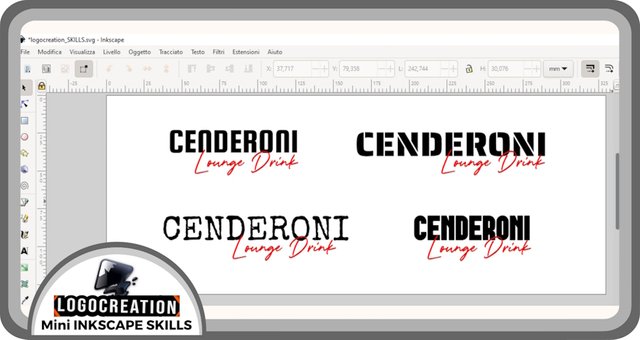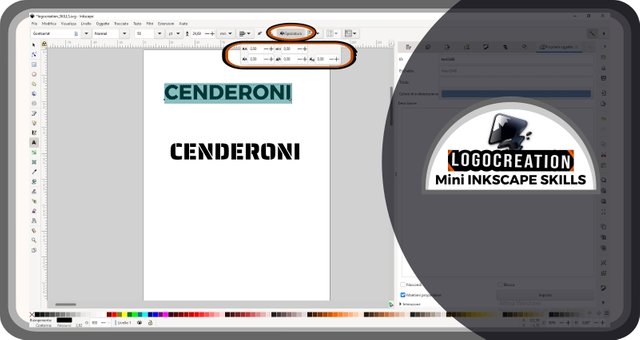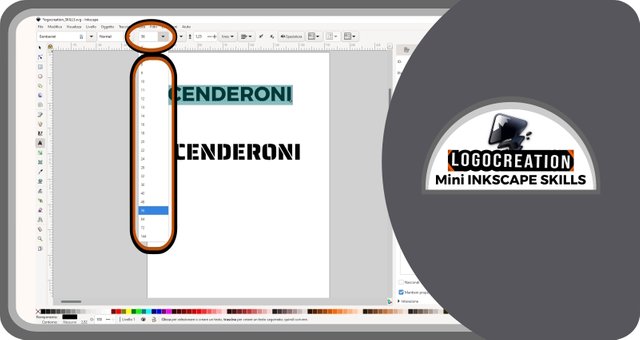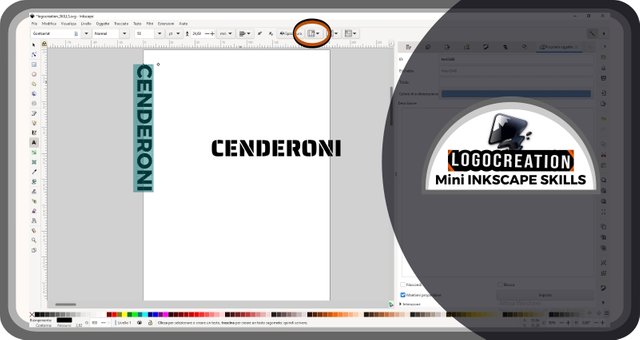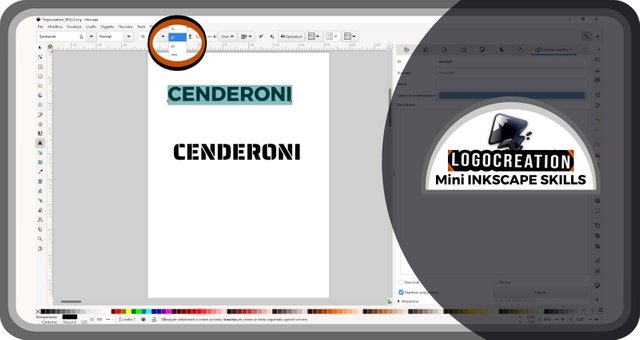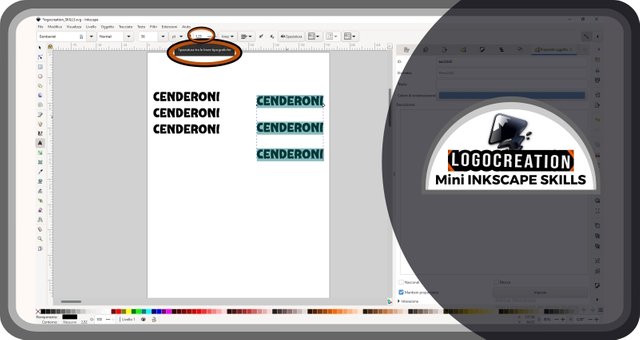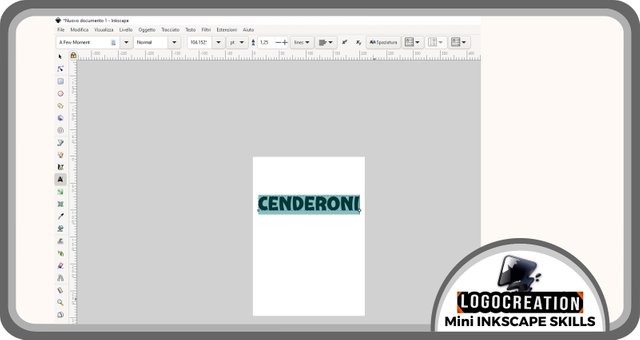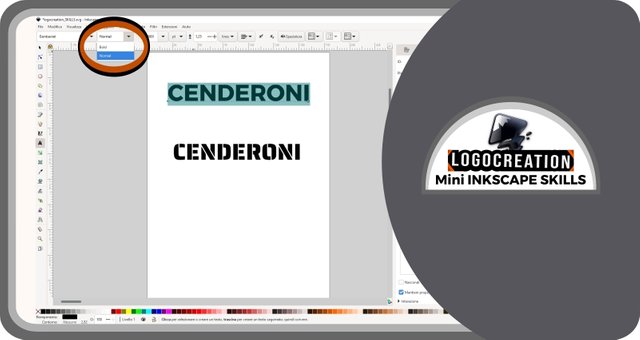
LOGOCREATION - Mini INKSCAPE SKILLS: FONT e CARATTERI TIPOGRAFICI [ITA-ENG]
Oggi torno con il primo vero episodio del mio spazio dedicato alla costruzione di graphic design e all'uso di Inkscape. Un paio di settimane fa ho lanciato l'argomento con un post introduttivo che trovi CLICCANDO QUI. Al suo interno puoi avere notizie riguardo i due fondamenti di questa specie di rubrica:
1. Creazione di loghi ipotetici a titolo di esempio
2. Utilizzo del programma di grafica vettoriale Inkscape
Non torno a ripetere tutto ciò che puoi trovare là, ma sostanzialmente il mio articolo cercherà di mostrare alcune della azioni di base di Inkscape durante la creazione di un logo immaginario; un logo che spesso avrà caratteri giocosi e pertanto invito a non prendere questa caratteristica come volontà di offendere qualcuno (cosa che assolutamente non è nell'intenzione di questi post).
Insomma, procediamo.
LOGO SEMPLICE – Usare i CARATTERI TIPOGRAFICI in Inkscape
Per questo primo appuntamento ho pensato a un logo composto da soli elementi testuali, usando i cosiddetti CARATTERI TIPOGRAFICI, anche definiti FONT. Che cosa indicano questi termini?
Il CARATTERE è ogni elemento comunicativo tra quelli che noi usualmente utilizziamo nella lingua scritta (per intenderci: le lettere, i numeri, la punteggiatura, eccetera). Se noi tracciamo una "a", ecco, quella è un carattere presente in molte lingue scritte occidentali.
Il (o secondo alcuni la) FONT indica invece l'insieme di caratteri tipografici tracciati con una certa morfologia, o ancor meglio con quello che potremmo definire "stile". Questo perché, per esempio, la lettera "a" può essere disegnata in vari modi che mantengono la morfologia fondamentale della lettera "a" ma che la rendono diversa da quella tracciata in uno stile differente. Per questo, quando i caratteri tipografici hanno invaso il mondo digitale, la parola font è stata utilizzata per indicare il file di installazione di una famiglia di caratteri disegnati nello stesso stile.
Questa distinzione netta delle due parole è però stata sconvolta, e – quando utilizzano la locuzione "CARATTERI TIPOGRAFICI" - le persone non stanno indicando gli elementi singoli, bensì il concetto di font (insieme dei caratteri di una data famiglia tracciata seguendo uno stile).
Quindi, per concettualizzare: il "carattere" non è un "font", ma spesso il "font" viene anche chiamato "carattere tipografico" (o, in taluni casi, semplicemente "carattere").
Detto questo... come creare un logo testuale in Inkscape?
Prima di tutto, è bene avere qualcosa da scrivere. Poi, è necessario aprire l'applicazione desktop Inkscape e cercare il tasto apposito visibile sulla finestra che si aprirà a centro schermo. La schermata base di Inkscape è solitamente una pagina centrale in A4 di colore bianco, con uno spazio intorno di colore grigio nel quale possiamo fare qualsiasi cosa vogliamo, ma che verrà perso se decideremo di utilizzare alcune tipologie di salvataggio (ma questo lo vedremo in futuri articoli).
Il tasto che dobbiamo cercare per iniziare a tracciare il nostro testo si trova alla nostra sinistra, a circa metà della colonna verticale che rimane su questo lato dello schermo; il PULSANTE TESTO è contraddistinto da una specie di lettera A maiuscola vicino a un'asta verticale.
Dopo aver portato il cursore (la freccetta) al di sopra del tasto e aver cliccato con il pulsante sinistro, saremo pronti per iniziare. Dobbiamo quindi spostarci al centro della pagina e cliccare di nuovo con il pulsante sinistro. Poi dobbiamo spostarci sulla tastiera e digitare ciò che vogliamo. Nel mio caso, la parola che avevo pensato per dare un nome al mio logo era "CENDERONI".
Come avrai visto dall'immagine sopra, la parola che abbiamo scritto sulla pagina è una parola formata da lettere (caratteri) tracciati in un certo stile. Questo stile è determinato dal font che abbiamo scelto. Ma nell'esempio che ti ho mostrato, il font non lo abbiamo scelto noi, poiché era quello preimpostato all'apertura del programma.
Mettiamo che questo stile non ci piaccia: cosa fare?
Semplice, dobbiamo CAMBIARE FONT.
Per cambiare font è necessario prima di tutto aver selezionato il "pulsante testo", poi aver portato il cursore sulla parola che abbiamo tracciato, all'una o all'altra estremità; poi cliccare e tener cliccato il pulsante sinistro, muovendo il cursore fino all'estremità opposta. In questo modo, avremo SELEZIONATO IL TESTO su cui vogliamo agire.